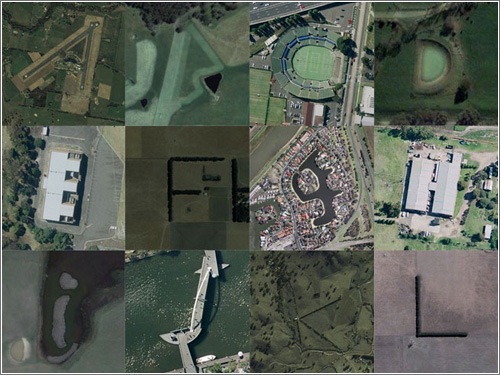
Tipografía con Google Maps
Alguien dedicó su tiempo a buscar en Google Maps formas que representen todas las letras del abecedario en el estado de Victoria, en Australia.